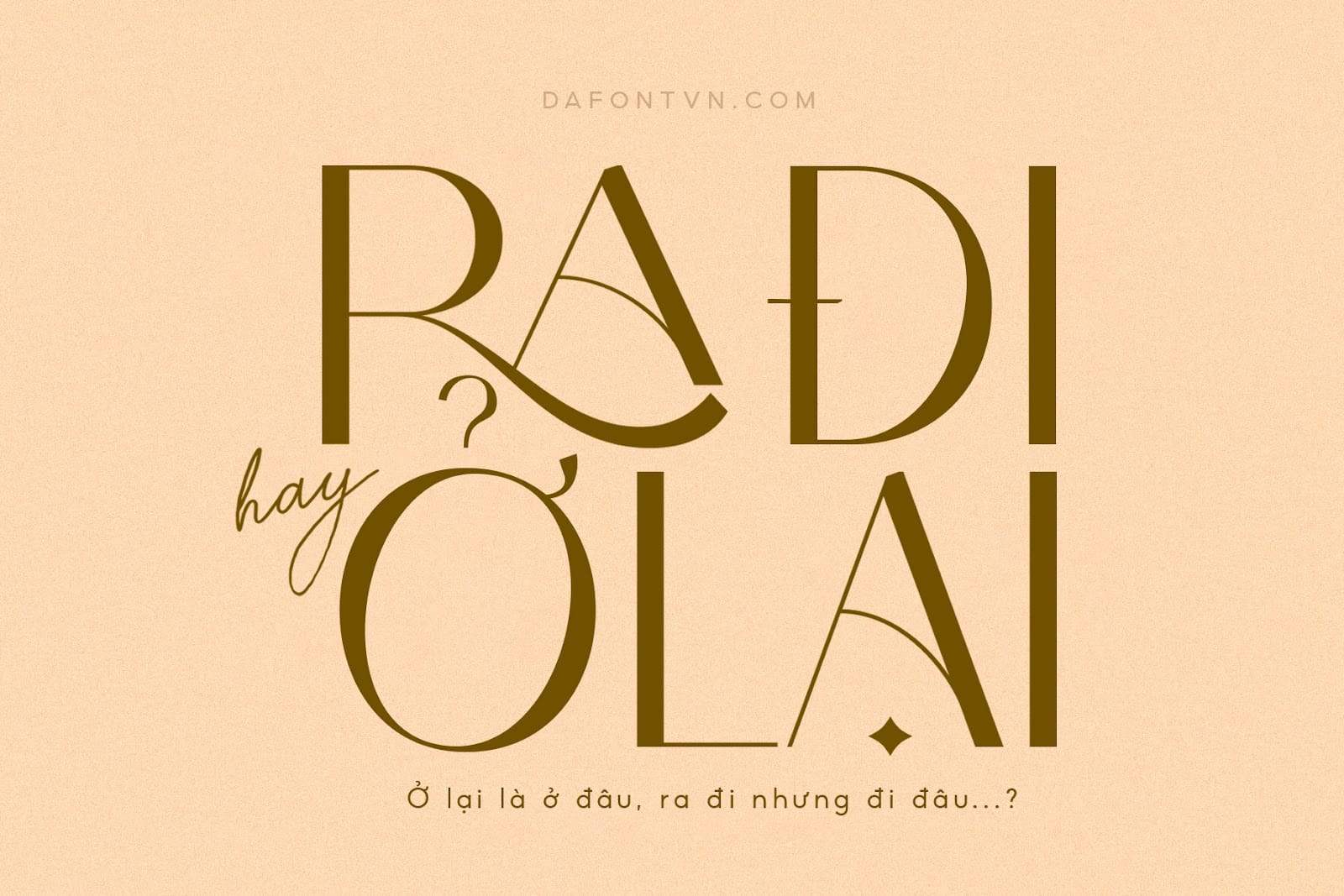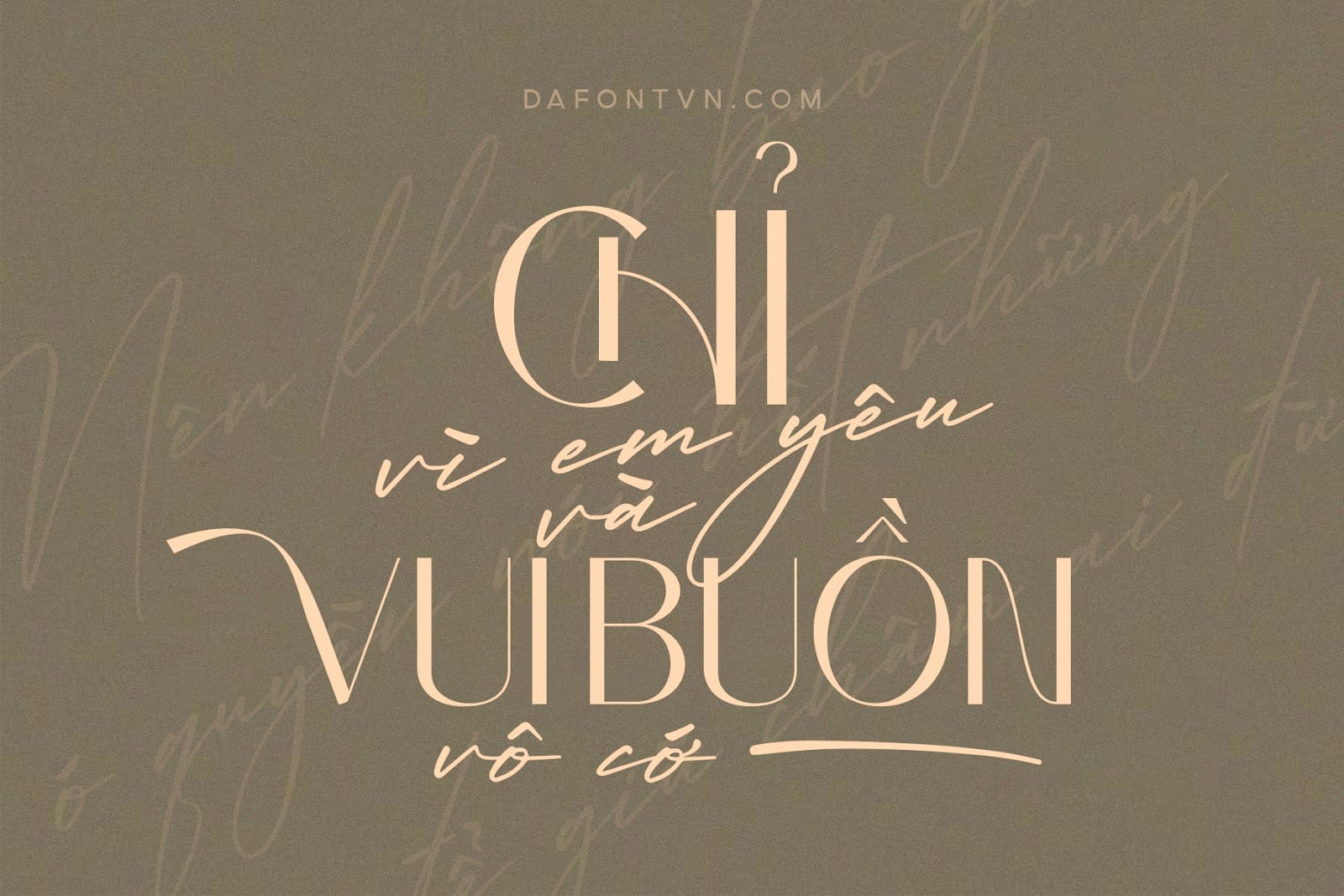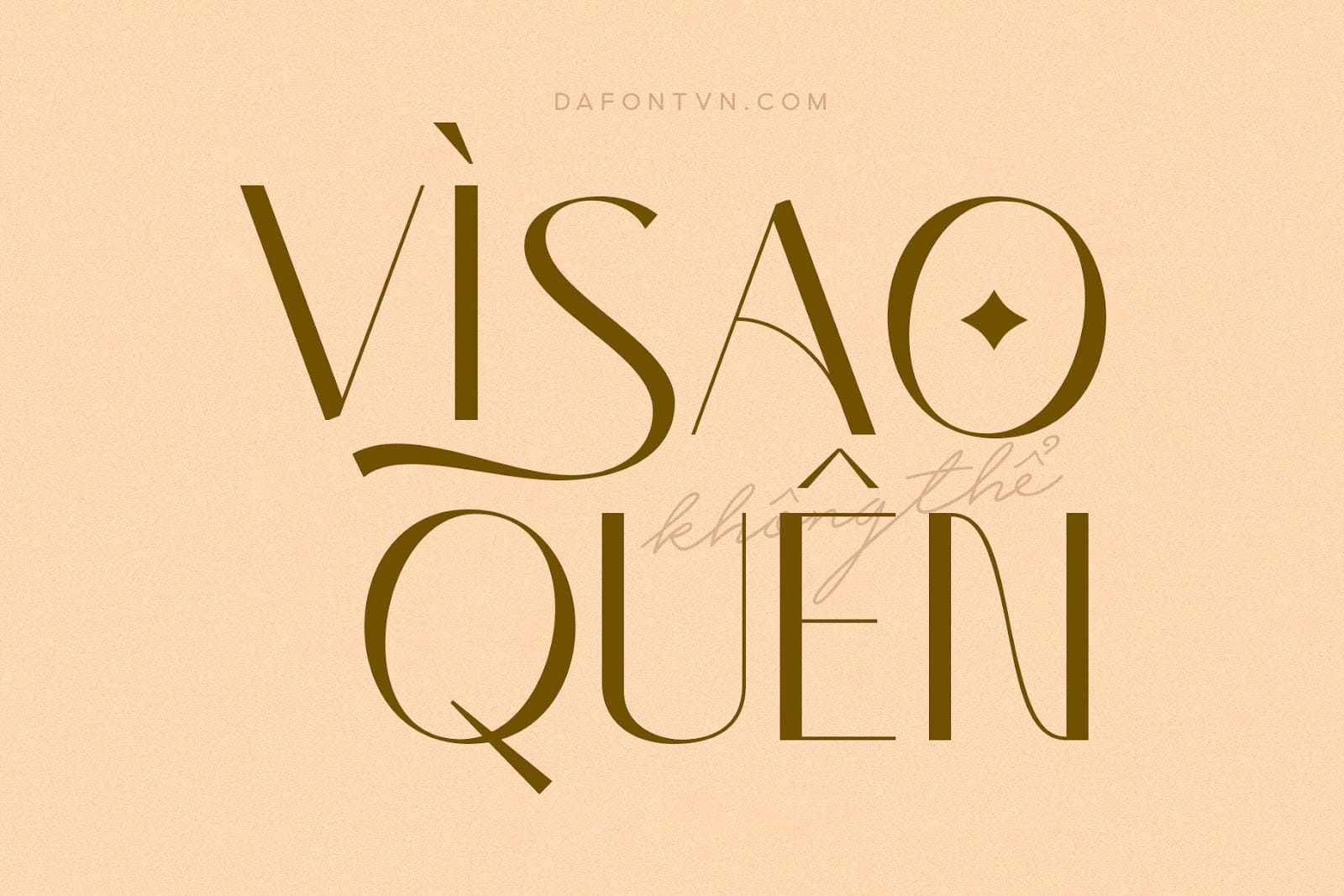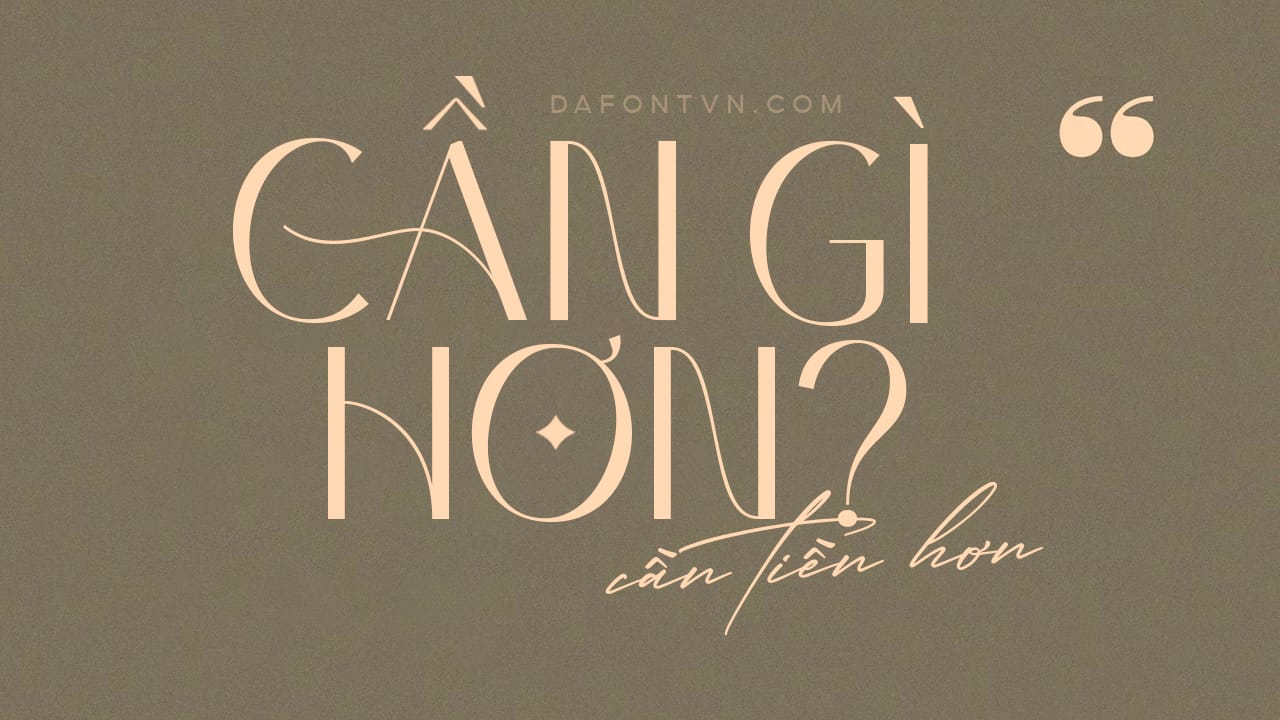
Calathea Font – 1 kiểu chữ thanh lịch sang trọng và hiện đại. Font Calathea được lấy cảm hứng từ những thiết kế hiện đại mang phong cách ấn tượng với các nét chữ được vẽ tỉ mỉ, đi kèm với các chữ ghép và chữ thay thế sẽ làm cho font trở nên ấn tượng hơn để sử dụng trong nhiều dự án khác nhau như thời trang, làm đẹp, tạp chí, nhiếp ảnh, giới thiệu sản phẩm, typography…
Font Calathea Việt hóa đầy đủ, kerning, chỉnh sửa, tối ưu và mã hóa PUA để sử dụng dễ dàng trên bất kỳ phần mềm nào. Để sử dụng các glyph các bạn có thể sử dụng Photoshop hoặc AI nhé.